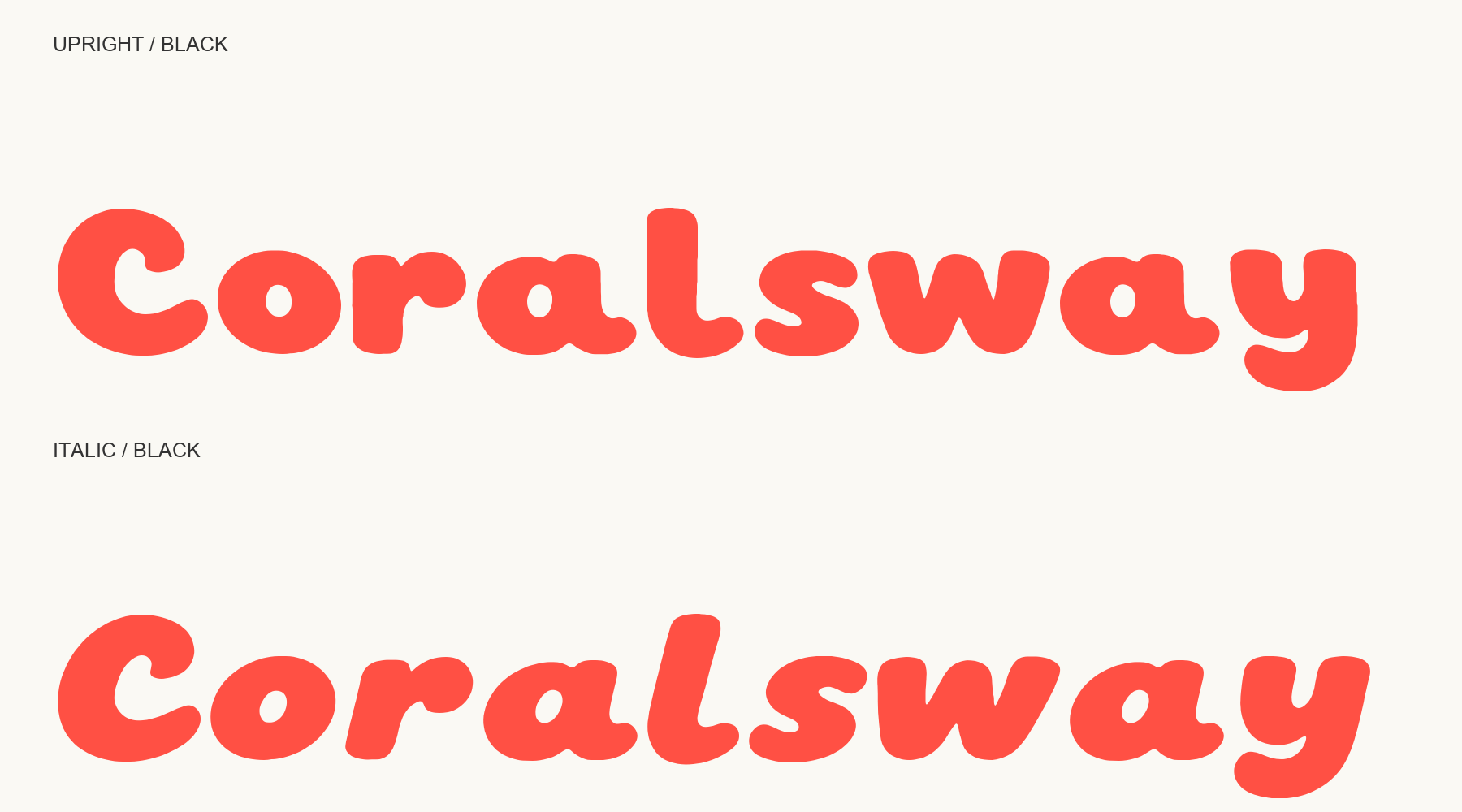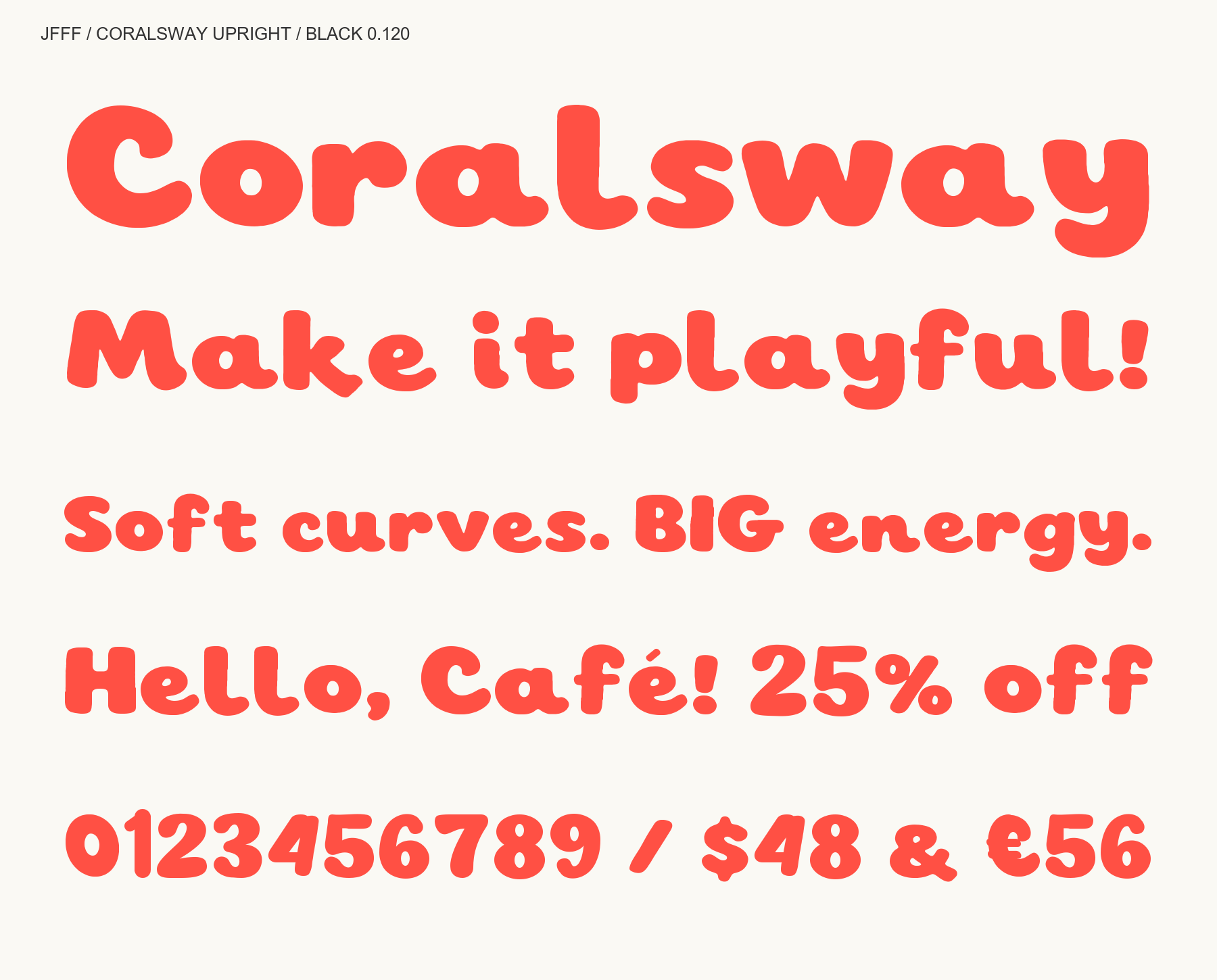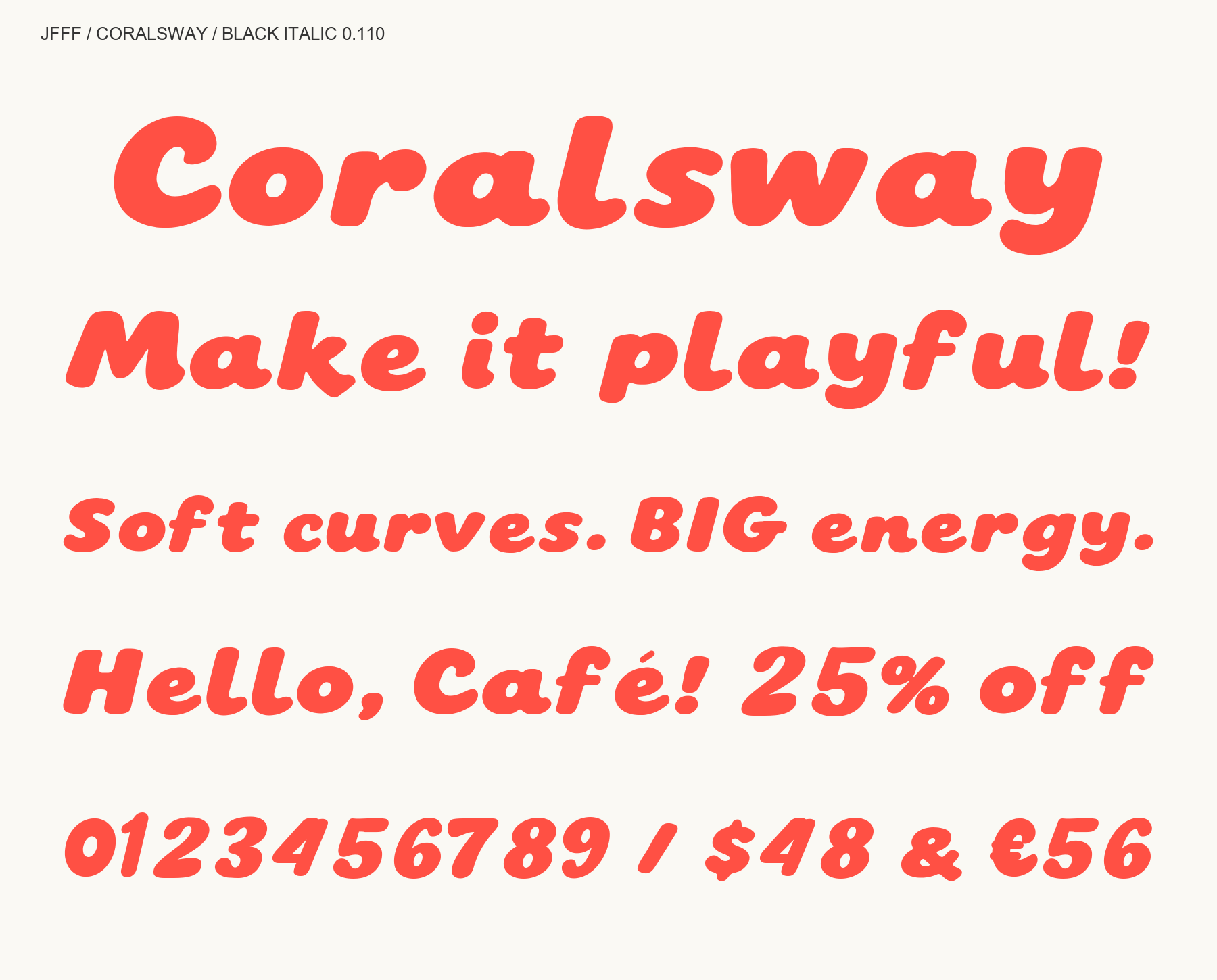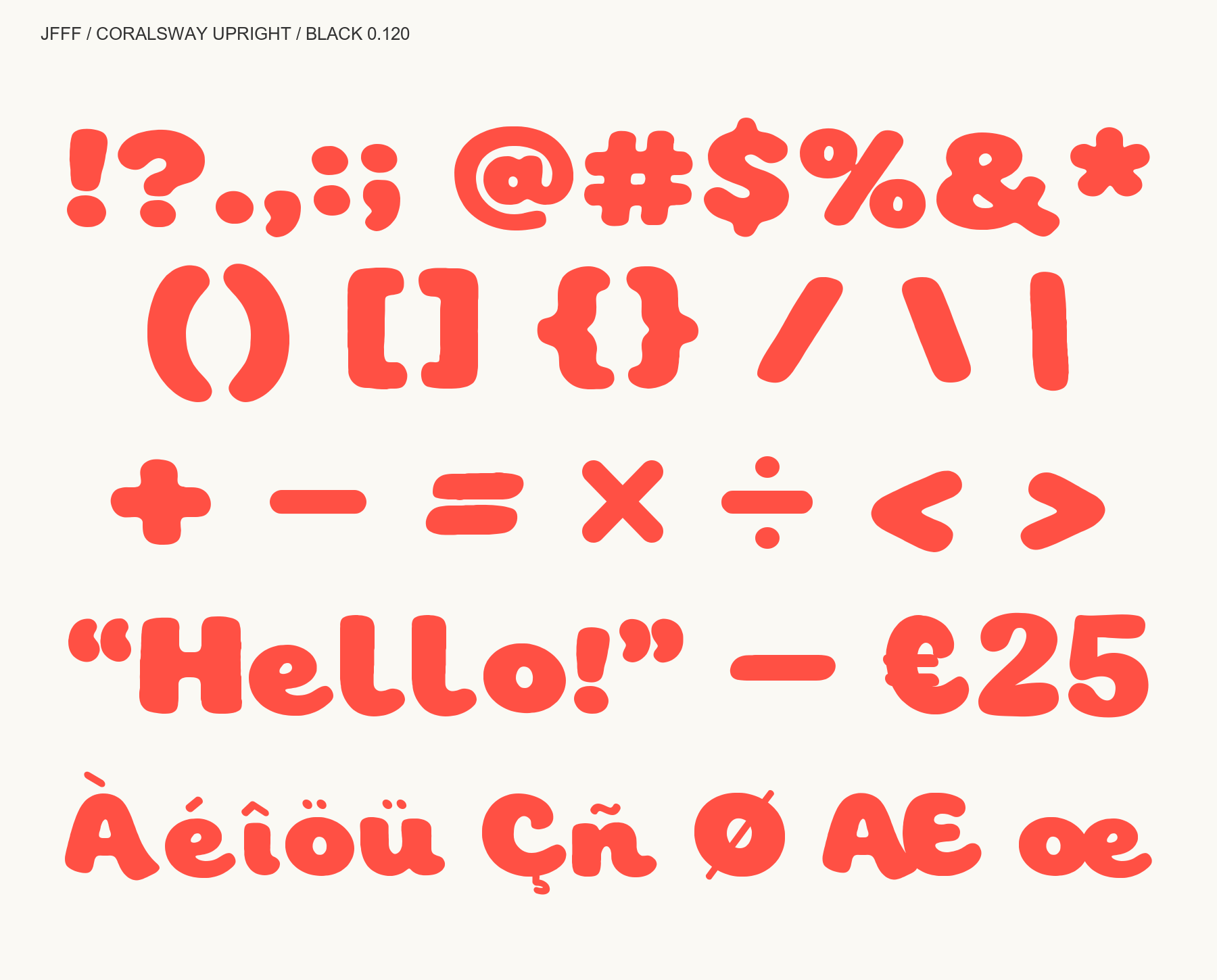
Latin only. No Hangul.
Coralsway는 둥근 끝과 두툼한 획, 한 층 구조의 a·g가 특징인 디스플레이 폰트 패밀리입니다. 하나의 ZIP에 두 스타일이 모두 들어 있습니다: Upright Black 0.120(직립) + Black Italic 0.110(기울임). 각 스타일은 라틴 330자(공백 2개 포함)를 지원하며, TTF·WOFF2 파일과 SIL OFL 1.1 라이선스를 제공합니다. 다운로드 후 원하는 스타일을 설치하여 선택하세요. 직립 버전은 330자 확대 문자표 검토 후 기호 31자의 잔여 기울기를 수정했습니다. 64px 이상 제목용으로 권장합니다. 한글은 포함하지 않습니다. 전체 커닝 및 운영체제별 검수는 추가 진행 대상입니다. 사이트의 입력 미리보기는 기울임 스타일이며, 갤러리에서 두 스타일을 비교할 수 있습니다.